타이포그래피는 글자들의 아름다운 그룹이다
위의 인용구는 Georgia, Big Calson, Verdana 등의 유명 서체들을 제작한 영국의 대표적인 타입 디자이너, 매튜 카터가 한 말입니다. 아무리 한 글자, 한 글자가 아름답게 디자인되더라도 그 글자들이 모였을 때 아름답지 않다면 의미가 없다는 말이죠.
글자의 간격 조정은 글자들이 텍스트로서 읽히고, 사용되기 위한 가장 마지막 단계입니다.
따라서 글자의 간격을 조정하는 스페이싱(Spacing)은 폰트를 제작하는 데 있어서는 글자의 디자인만큼이나 중요한 프로세스라고 할 수 있죠. (실제로 폰트를 제작할 때 많은 폰트 디자이너들이 가장 많은 시간을 투자하는 작업이기도 합니다.)
위의 이미지는 한 디자이너가 "만약 Helvetica의 커닝 설정이 엉망이었더라면?"라는 질문으로 시작한 Hellvetica라는 프로젝트의 일부분입니다. 글자의 간격 조정이 얼마나 중요한지 감이 오시나요:)
이번 글에서는 글자들의 형태에 따라 어떻게 간격이 조정되어야 하는지는 예시와 함께 설명드리려고 합니다. 이론적인 부분부터 실제 폰트의 예시를 보여드릴 테니 천천히 따라 해 보세요!
1. 모든 형태는 다른 간격을 가진다
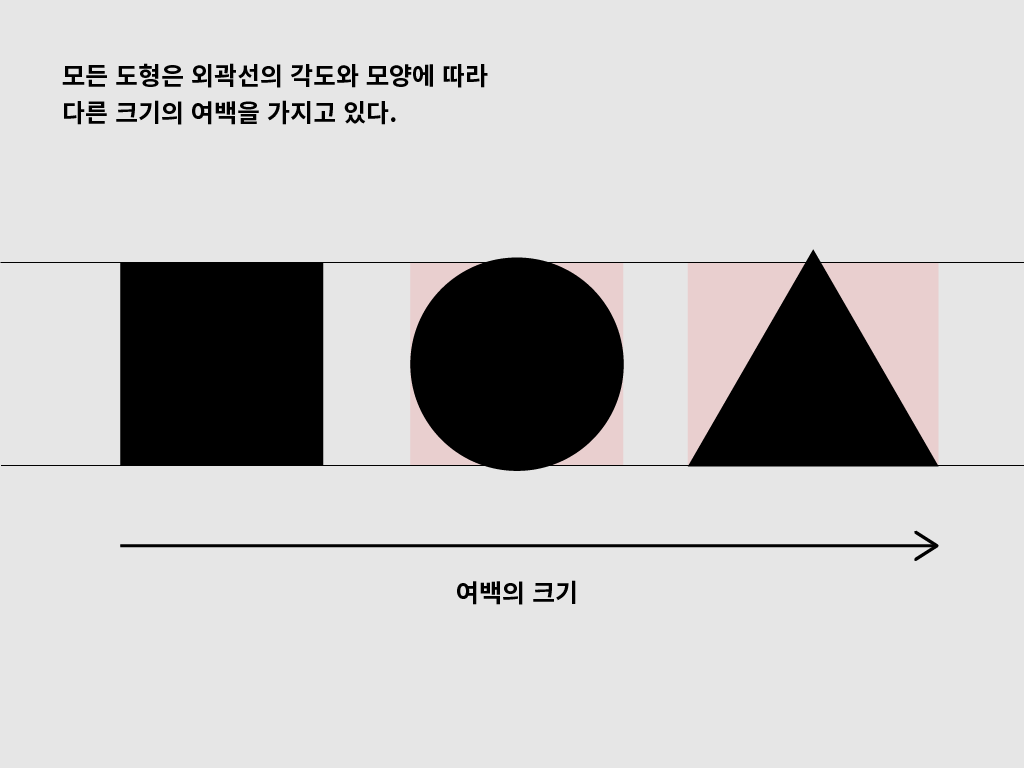
우선 영문 알파벳에서 쉽게 찾아볼 수 있는 사각형, 원형, 삼각형을 예시로 들어보겠습니다. 위아래의 기준선에 맞춰져 있는 사각형은 여백 없이 꽉 차있는 형태지만, 원형과 삼각형은 붉은 공간과 같은 여백이 남게 됩니다. 도형의 외곽 형태가 사선으로 길어질수록 이 여백의 공간 또한 커집니다.
다음 스텝으로 가기 전에 글자의 간격 조정에 필요한 용어를 짚고 넘어가 보겠습니다.
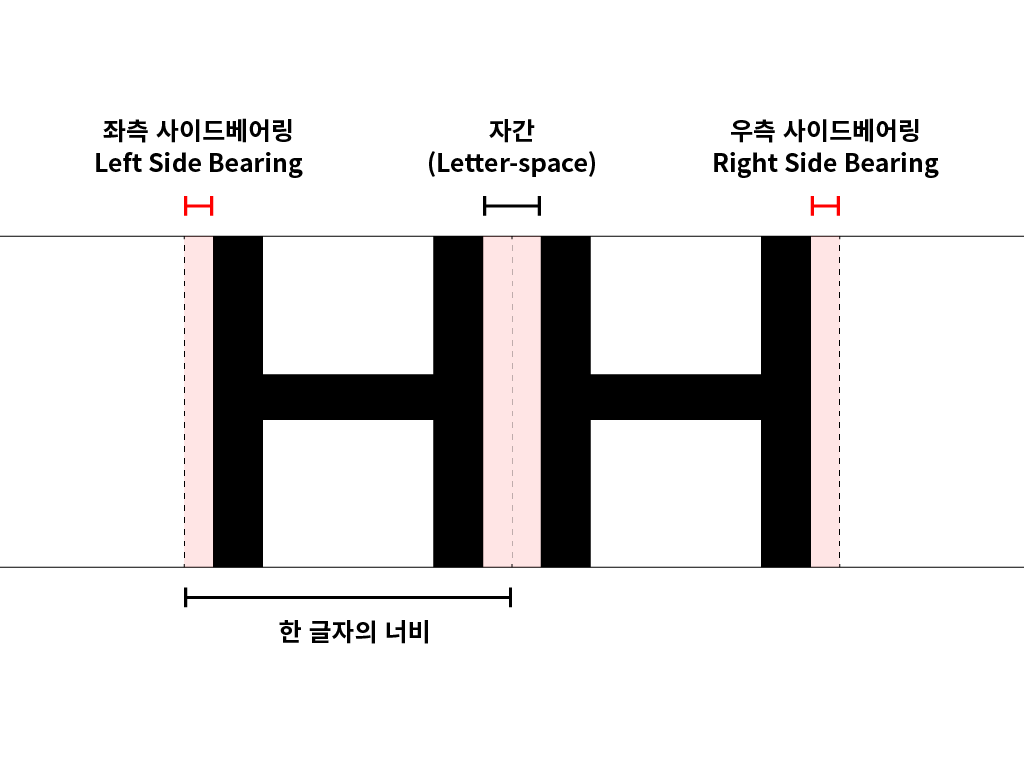
디자인하실 때 텍스트를 분명 왼쪽 라인에 여백 없이 붙였는데도 여백이 남아있던 경험이 있으신가요? 바로 글자에는 좌우로 추가적인 공간인 "사이드베어링(Side Bearing)"이 존재하기 때문입니다. (사이드베어링은 글자들이 서로 충돌하는 것을 방지해주는 역할을 합니다.) 좌우의 사이드베어링과 실제 글자 크기를 합쳐야 폰트에서 볼 수 있는 실제 한 글자의 너비가 됩니다.
설명드렸으니 이제 다시 위의 도형들로 돌아가 볼까요?
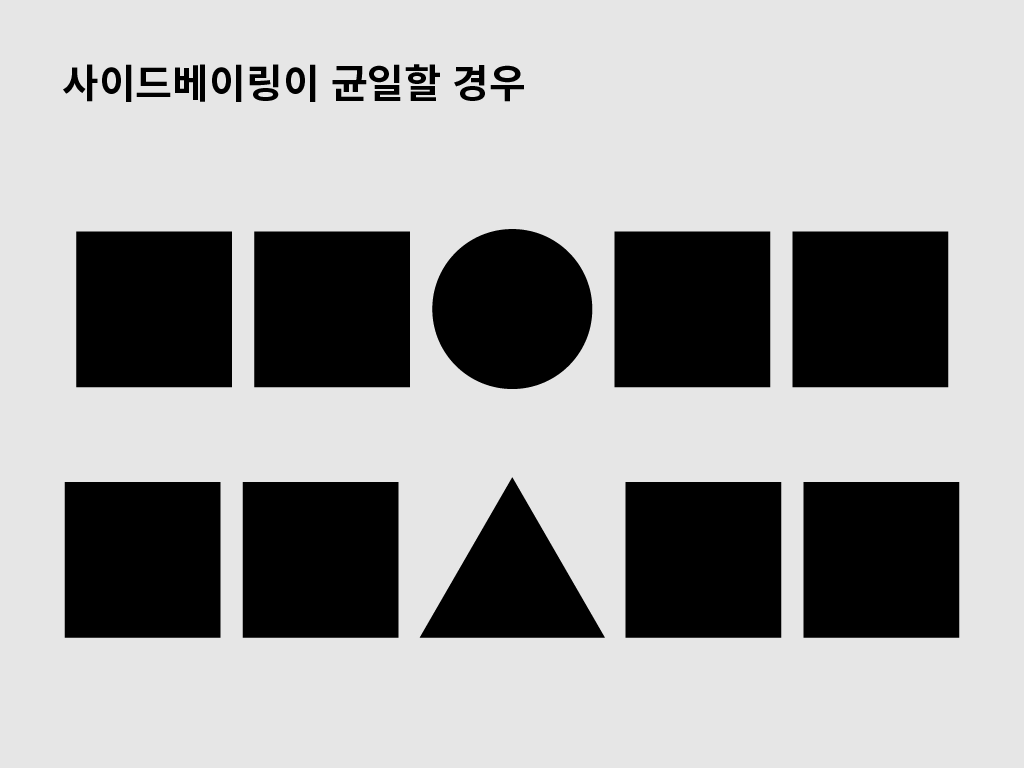
원형과 삼각형을 사각형 사이에 같은 간격으로 놓아봤습니다. 어떠신가요? 도형들이 일정한 간격으로 배치되어 보이시나요?
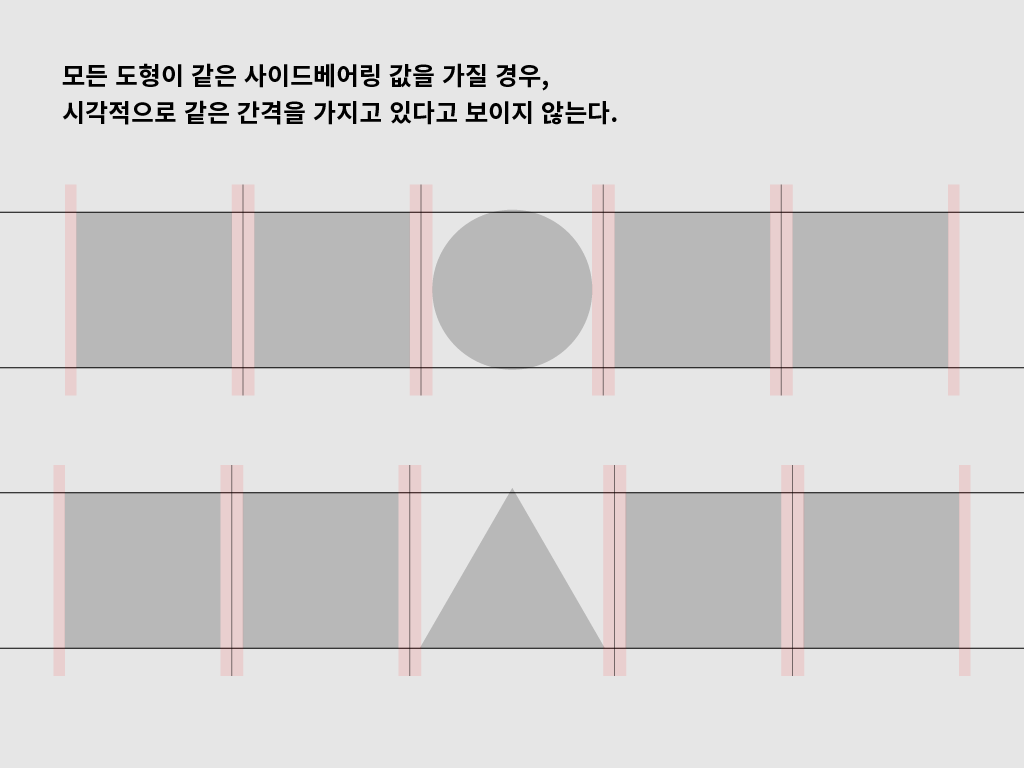
맨 처음 이미지에서 언급한 원형과 사각형의 여백 때문에 모든 도형이 같은 간격으로 위치하고 있음에도 불구하고 더 많은 공간을 차지하는 것처럼 보입니다. 일종의 착시 현상이죠.
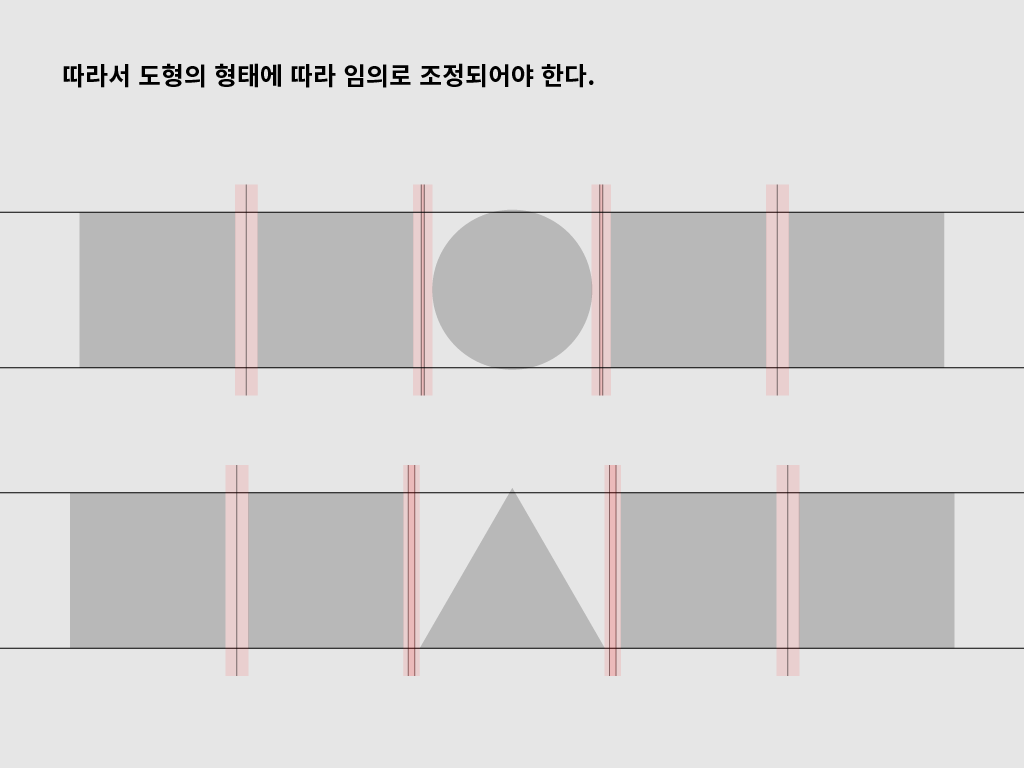
이를 방지하기 위해서 사각형의 사이드베어링과 원, 삼각형의 사이드베어링의 일부분이 겹쳐지게 해 봤습니다.
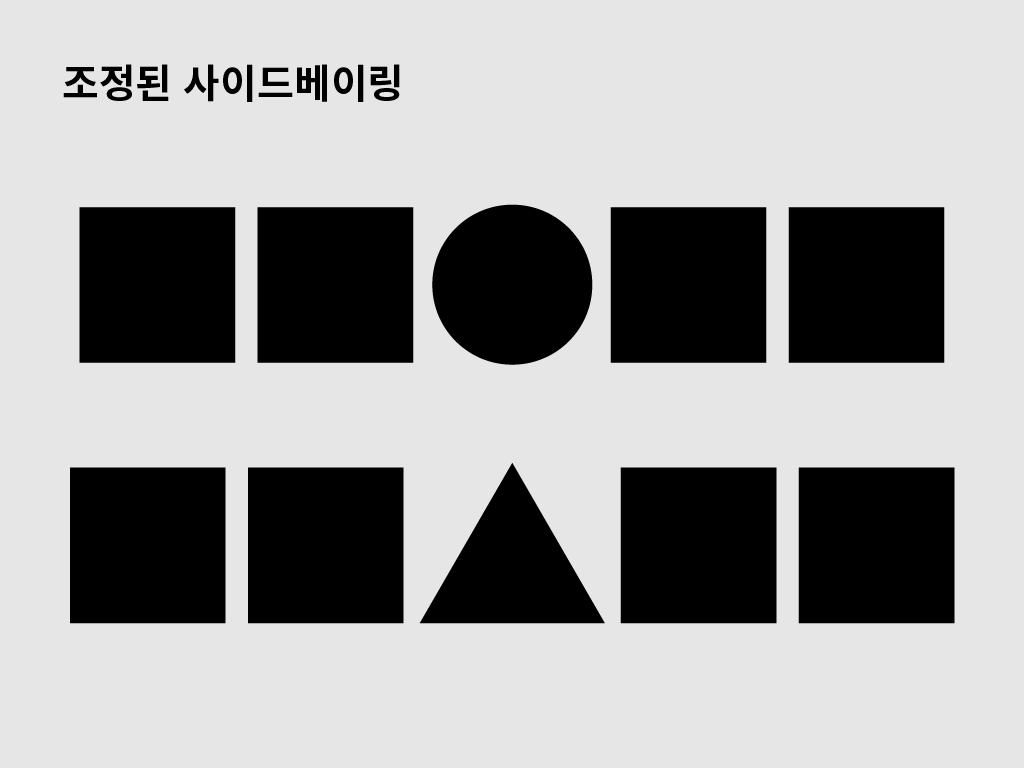
짜잔! 어떤가요? 분명 이전의 이미지보다는 좀 더 일정한 간격으로 보입니다.
이제 실전으로 넘어가 봅시다!
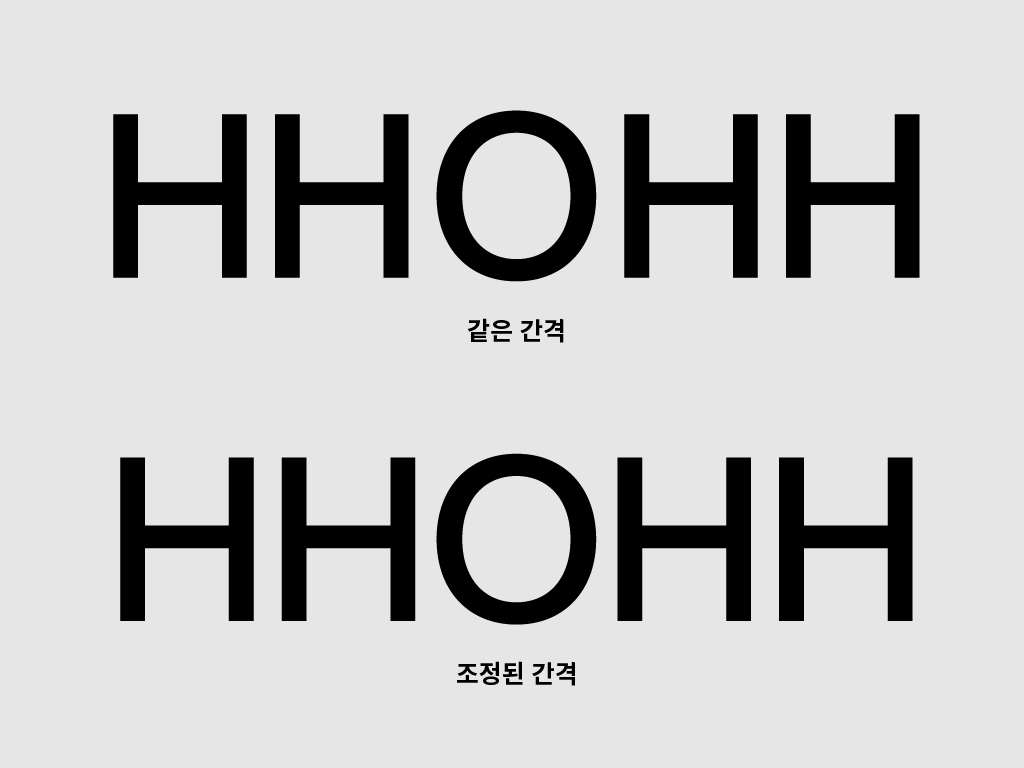
이 이미지는 위에 기본 도형들을 가지고 했던 실험 그대로 실제 글자에 적용시킨 예시입니다. 글자로 간격을 조정해보니 더 와 닿아 보이시지 않나요?
2. 간격의 기준 세우기
이론을 배웠으니 이제 실제 알파벳들이 어떤 기준으로 간격을 정하는지 알아볼 차례입니다. 이번 글에서는 영문의 대문자 26자와, 소문자 26자의 간격 조정 방법을 설명할 예정입니다. 대문자부터 한번 볼까요?
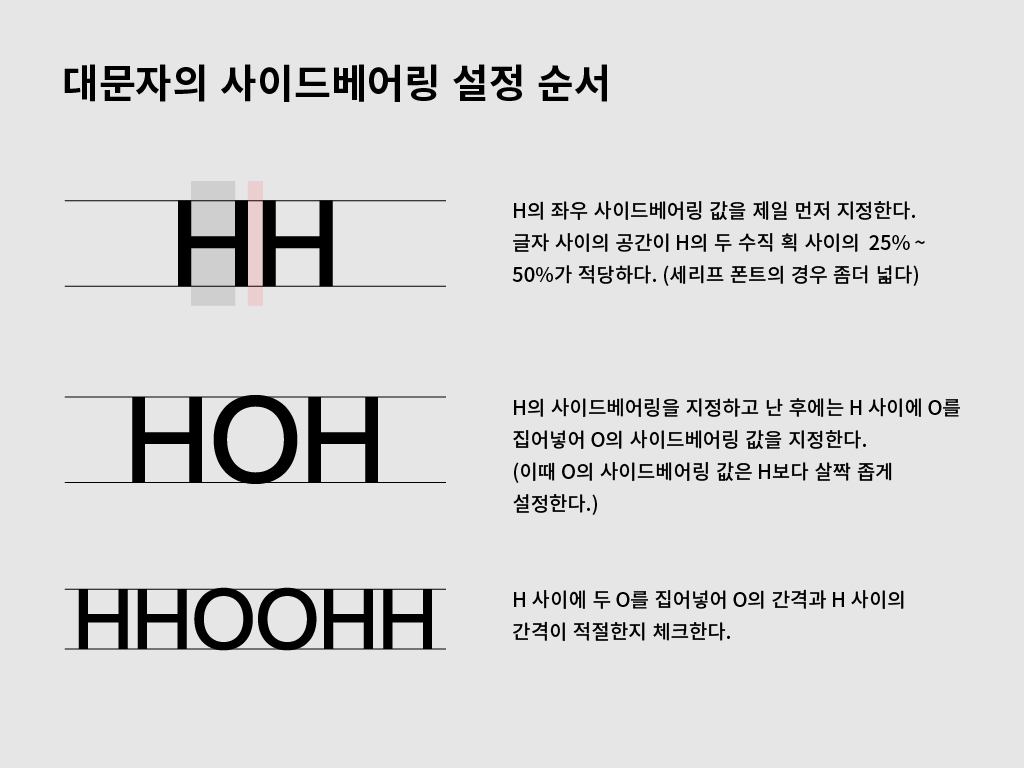
대문자의 간격 조정은 H, O가 다른 글자들의 간격을 조정하는데 기준이 됩니다. 폰트가 두꺼워질수록 H와 O의 간격이 줄어드는 것을 볼 수 있는데 이는 글자가 두꺼워질수록 H의 속공 간 또한 좁아지기 때문입니다. 또한 세리프 폰트는 글자의 외곽으로 튀어나온 세리프 때문에 산세리프 폰트보다 좀 더 많은 공간(50% 이상)을 할애합니다.
H와 O의 사이드 베어링을 지정했다면 이 둘 글자를 기준으로 다른 24자의 글자들 또한 사이드베어링 값을 지정할 수 있습니다. (위 이미지에서 숫자는 사이드베어링의 크기를 수치로 표현한 것이 아니니 오해하지 않으시길 바랍니다.)
아쉽게도 소문자는 대문자처럼 양옆이 수직선으로 뻗어 있는 글자가 없기 때문에 n과 o를 기준으로 삼습니다. n의 우측 사이드베어링은 커브가 존재하기 때문에 좌측의 사이드베어링보다는 살짝 좁게 조정합니다.
나머지는 대문자와 같이 조정하시면 됩니다. (a, g, s, z, f, t와 같은 글자들이 임의로 조정되어야 하는 이유는 폰트의 스타일에 따라 이 글자들의 모양이 너무 달라지기 때문입니다.)
휴... 다하신 거 같다고요?
글자의 간격 조정은 이제 시작입니다.
3. 커닝
글자의 간격을 조정하는 Spacing이 끝났다면, 글자의 양 사이드베어링으로는 해결되지 않는 글자들의 조합을 수정해야 하는 커닝 작업이 남아있습니다. 커닝 작업은 정말 많은 테스트를 거치며 반복적으로 확인해야 하기에 시간도 매우 오래 걸리고 피곤한 작업입니다. 요즘에는 기술이 좋아져서 Auto Kerning 같은 기능들도 있지만 완벽한 간격은 하나하나 수정해야 합니다.
우선 커닝의 예시부터 보고 넘어가겠습니다.
위의 Avenue라는 단어에서 A와 v, 그리고 e가 너무 떨어져 있는 것이 보이시나요? 아무리 사이드베어링 값을 적절하게 조정해도 위와 같이 서로를 거부하는 글자 조합들이 있습니다. 커닝을 적용하면 아래 단어처럼 단정하게 간격을 조정할 수 있습니다.
AT AV AW AY Av Aw Ay Fa Fe Fo Kv Kw Ky LO LV LY PA Pa Pe Po TA Ta Te Ti To Tr Ts Tu Ty UA VA Va Ve Vo Vr Vu Vy WA WO Wa We Wr Wv Wy